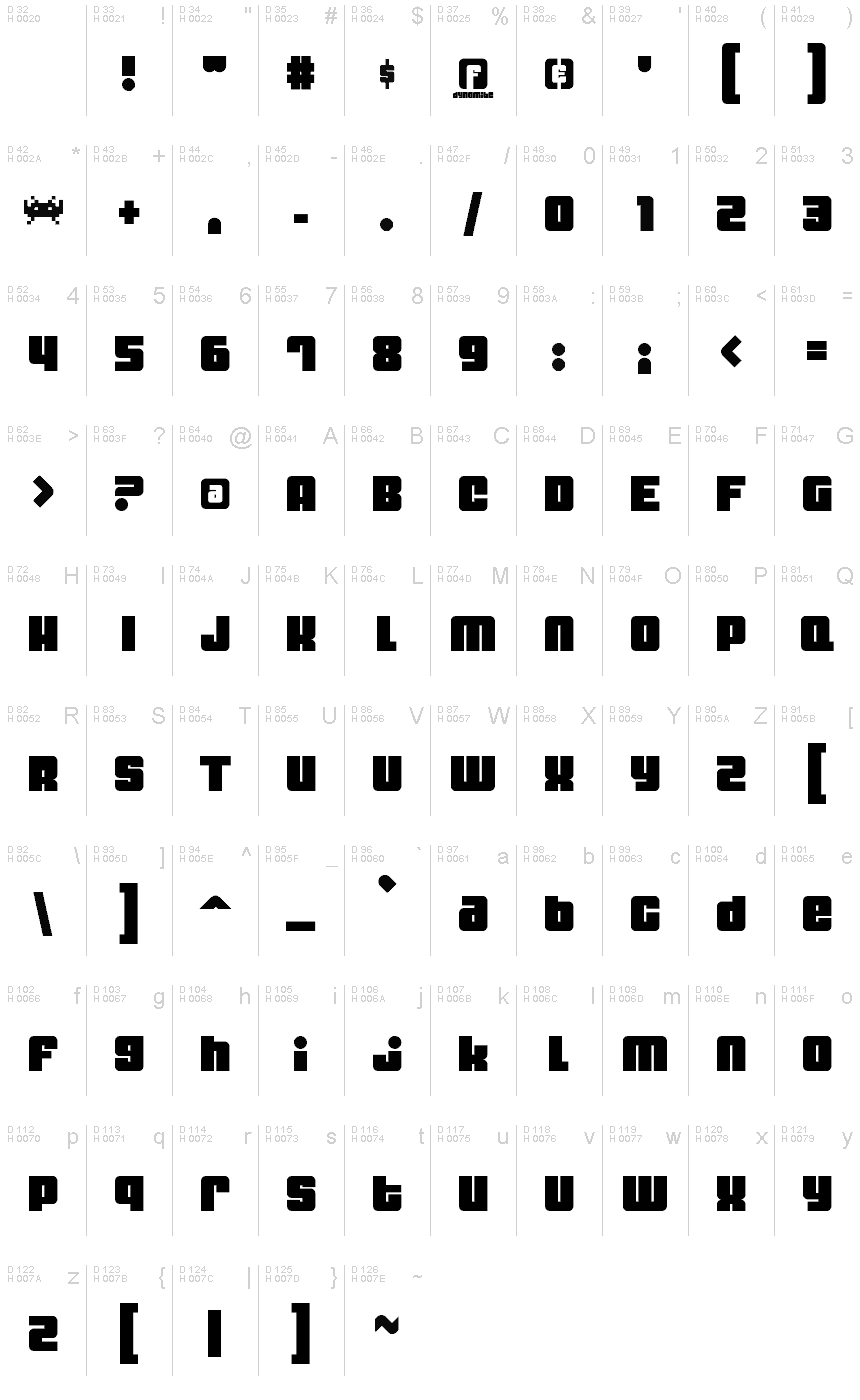
Font *Dynomite* od Fontalicious Fonts to nowoczesny i darmowy krój displayowy, który przyciąga wzrok grubymi, zaokrąglonymi blokami i ostrymi „wcięciami”, nadającymi każdemu słowu niemal inżynieryjną precyzję. Litery wyglądają jak wycięte z matowego plastiku lub odbite stemplem – są masywne, zwarte i pewne siebie, z futurystycznym rytmem, który pozostaje czytelny nawet przy bardzo ciasnym składzie.
Zastosowanie *Dynomite* w tytułach gier, plakatach sci-fi, brandingu technologicznym, grafikach esportowych, okładkach albumów, ulotkach czy miniaturach na YouTube zapewnia natychmiastowy efekt bez zbędnych udziwnień. Ten darmowy font najlepiej sprawdza się w dużych rozmiarach i krótkich frazach; jeśli układ wydaje się zbyt gęsty, zwiększ nieco światło między literami. Dla tekstów pomocniczych zestaw go z spokojnym krojem bezszeryfowym, takim jak Inter lub Helvetica.